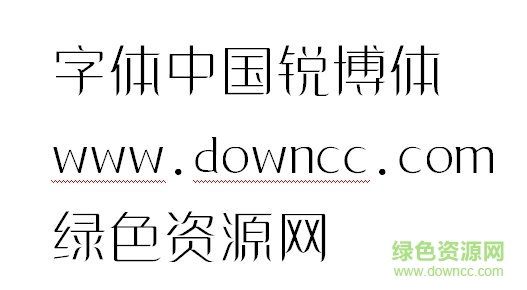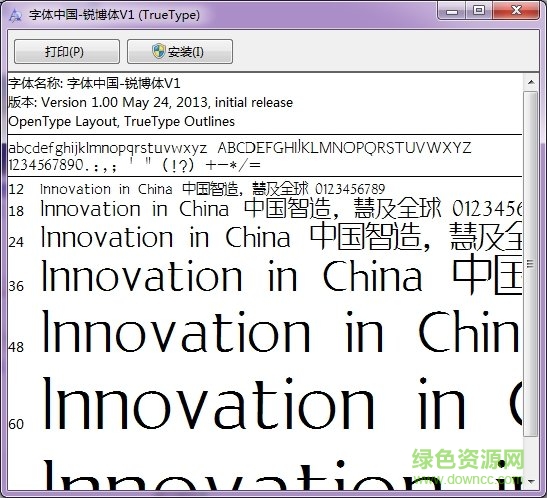
銳博字體是字體中國(guó)推出的一款細(xì)線中文系,纖細(xì)的造型讓字體顯得大方的體,本系列有v1和v2兩款字體,歡迎大家下載嘗試!
銳博體字體方中帶圓,筆畫(huà) 柔美光潔、粗細(xì)均勻、結(jié)構(gòu)美觀??捎糜趶V告設(shè)計(jì)字體、網(wǎng)頁(yè)設(shè)計(jì)字體、包裝設(shè)計(jì)字體、 屏幕顯示字體等。